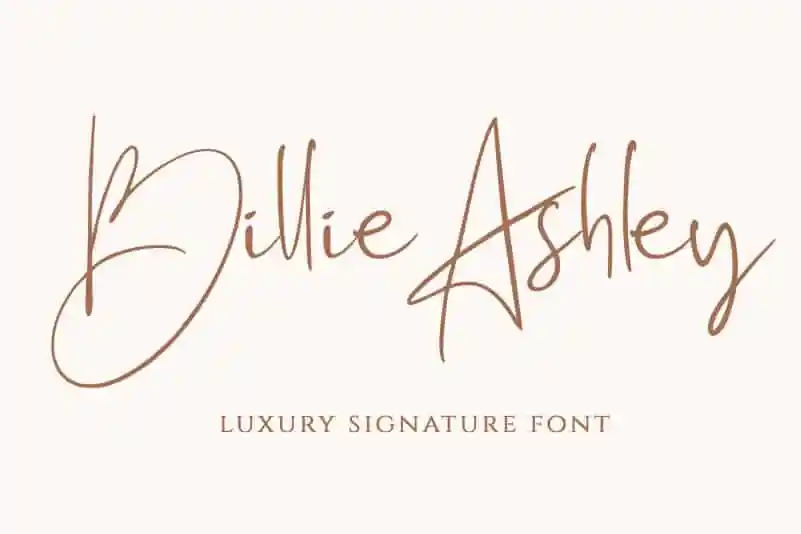
Billie Ashley Handwritten Font – Download Grátis
A fonte “Billie Ashley Handwritten Font” é uma elegante escolha para quem busca adicionar um toque de sofisticação ao seu design de marca ou aos detalhes de seus projetos pessoais. Essa fonte foi criada com técnicas de escrita manual, mantendo a essência autêntica e delicada do estilo moderno de script retrabalhado chamado Billie Ashley. Esta elegante opção é perfeita para um amplo leque de aplicativos, incluindo o uso em identidades visuais de marcas, assinaturas pessoais, convites de casamento ou até mesmo em outros projetos onde uma escrita cuidadosamente retrabalhada será atraente e diferenciadora. Com Billie Ashley na sua lista de fontes, você poderá personalizar qualquer projeto com estilo e elegância.